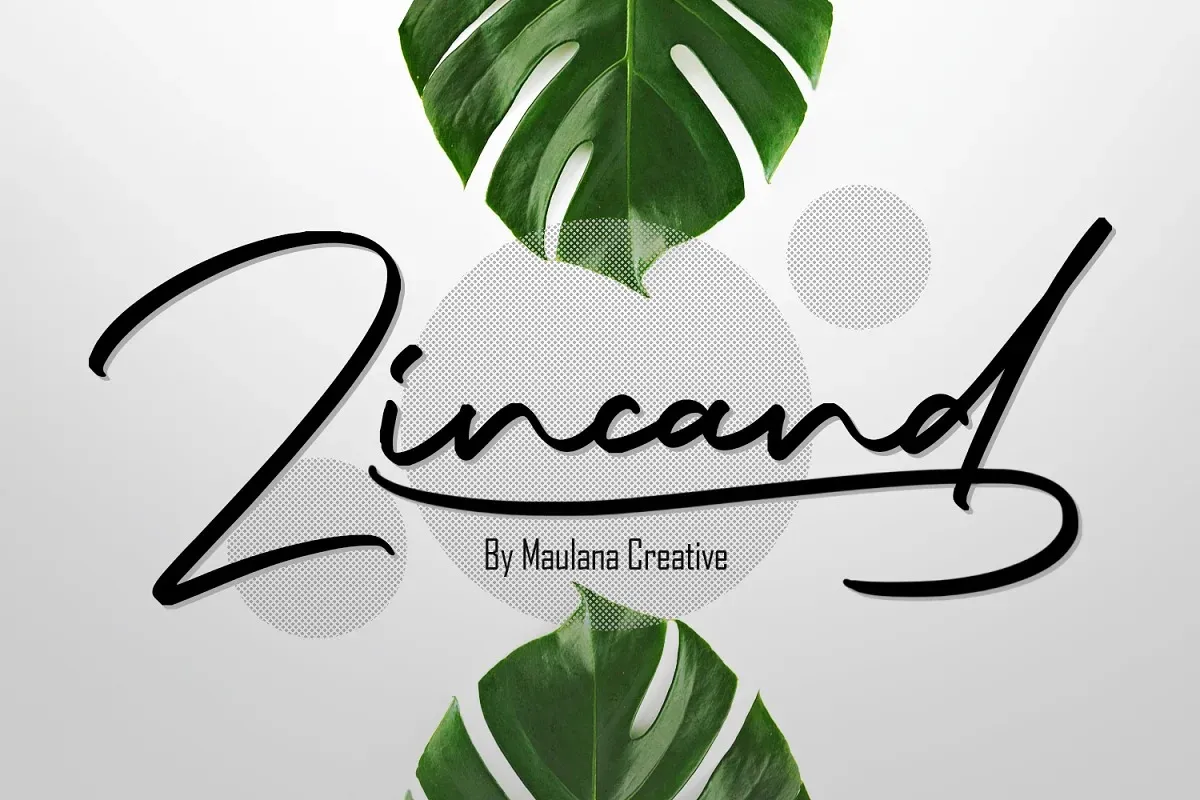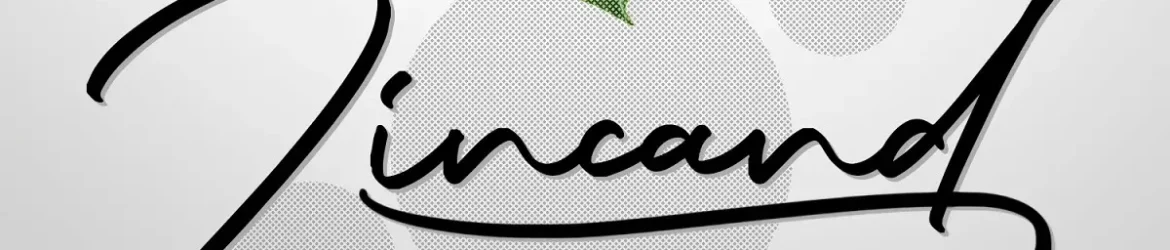
Esta fonte “Zincand” é uma elegante assinatura criada por Maulana Creative para quem busca um estilo rusticamente romântico. Inspirada nas rótulas e sinalizadoras usadas nos mercados de produtores locais, bem como nos eventos vintage com o clima da antiguidade que surgem frequentemente atualmente, esta fonte é perfeitamente adequada para uso em diversas aplicabilidades visuais. Seja como assinaturas, embalagens ou materiais de propaganda, este script tem uma grande capacidade de se adaptar a diferentes projetos, garantindo um toque único e personalizado. A fonte também combina bem com logotipos, letras do cabeçalho para websites, capas de livros e revistas, rótulos para roupas de moda e até mesmo em campanhas publicitárias e marcas de produto. Uma adição indispensável a qualquer designer que busca um toque sofisticado e autêntico em suas criações visuais.